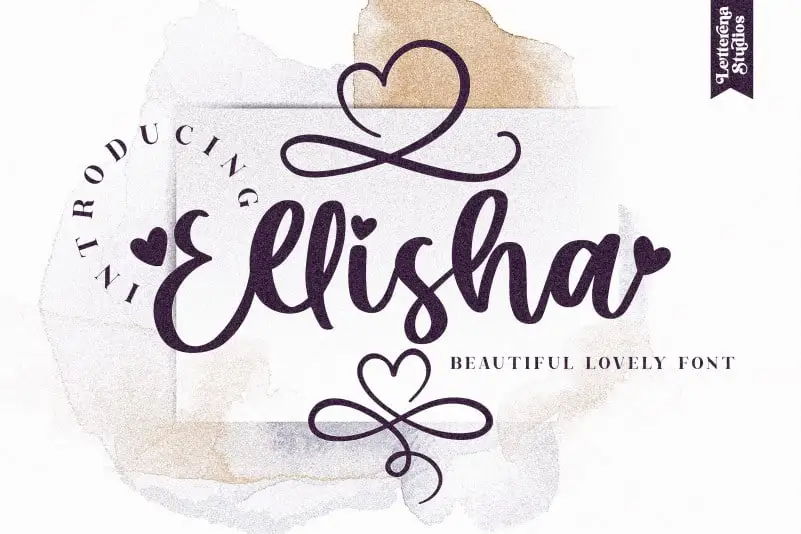
Ellisha Calligraphy Font – Download Grátis
A fonte “Ellisha Calligraphy Font” é uma delicada e elegante ilustração escrita a mão que certamente enriquecerá seu design. Seus traços distintos e bem arredondados fazem dela um verdadeiro trabalho de arte. Esta font é perfeita para quem procura algo sofisticado e único, capaz de criar designs memoráveis e estilosos. Adore essa fonte e a use como desejará para dar destaque a seus trabalhos visuais. Ela não só enriquece sua obra, mas também faz dela mais especial e única. Embarque nesta aventura designística com o “Ellisha Calligraphy Font”.